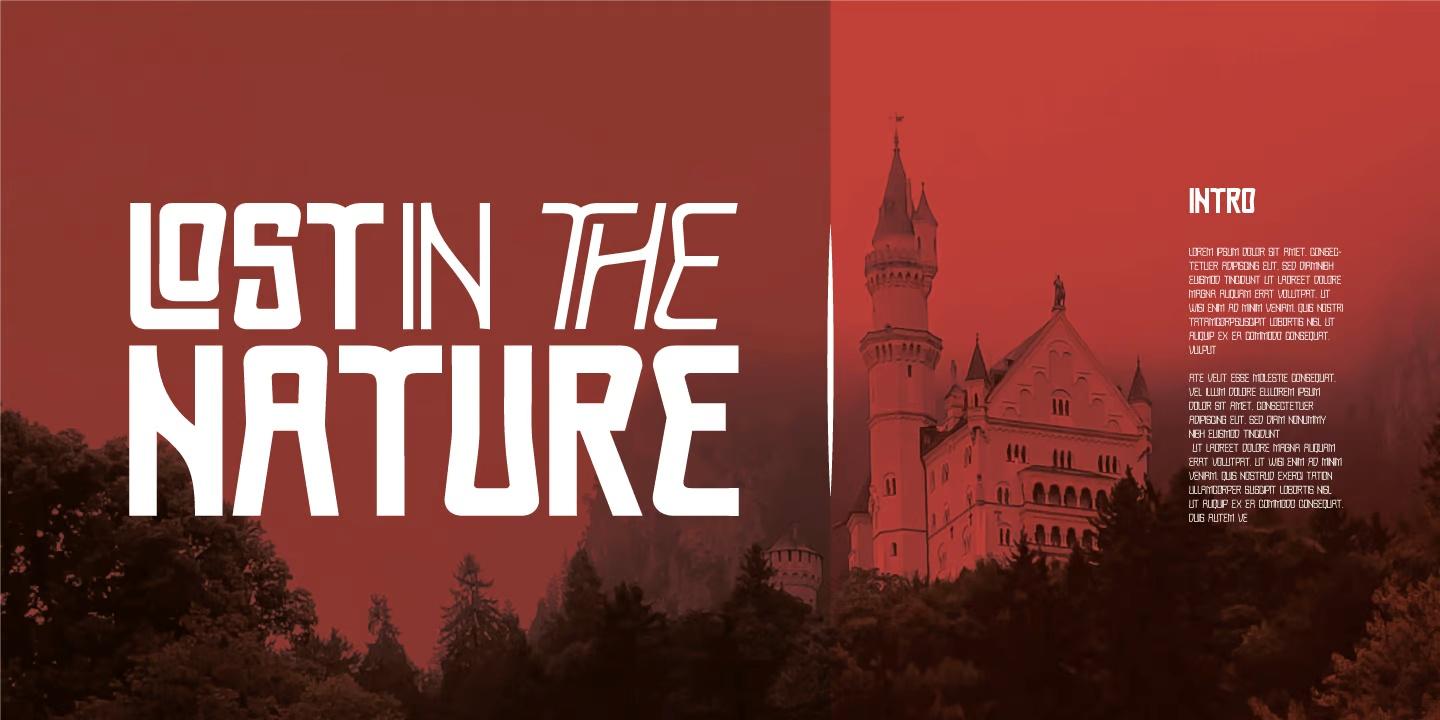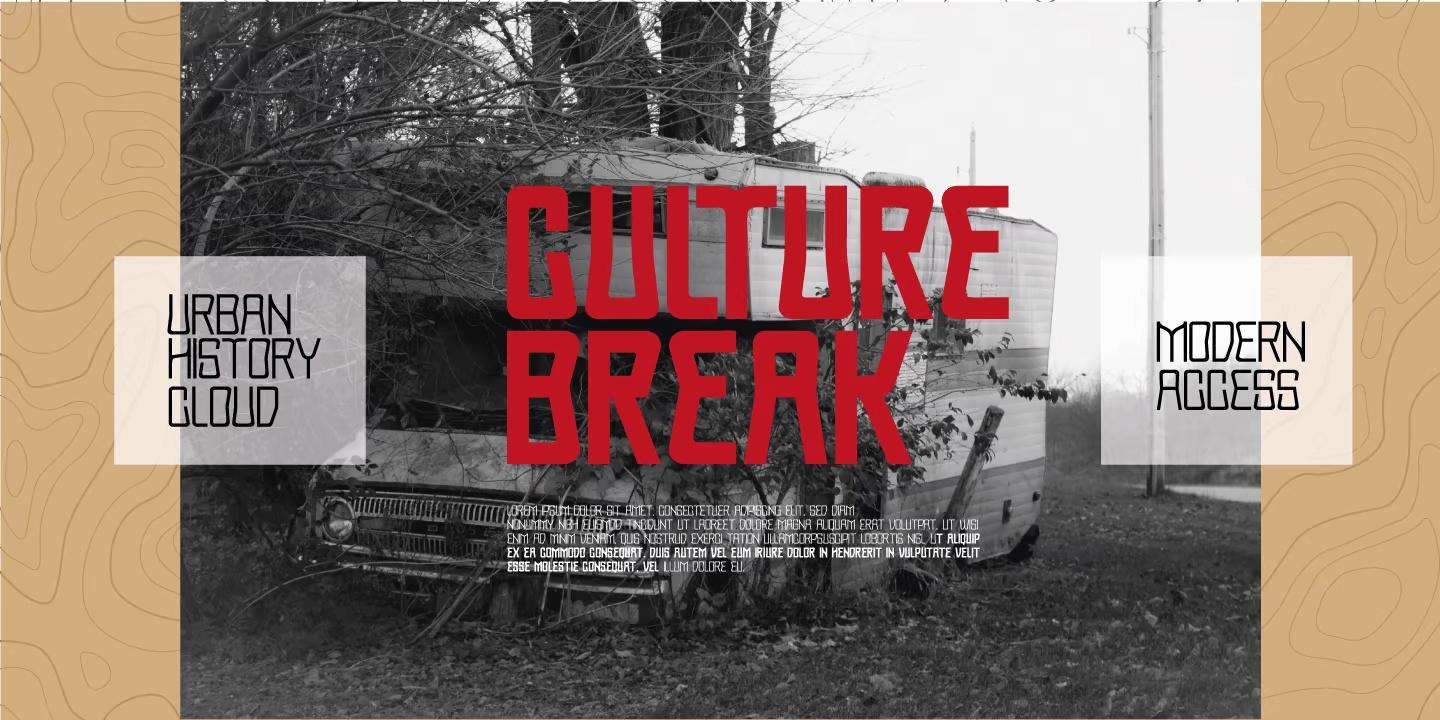
Proach Font
Description de Proach Font
Poarch est une police condensée propre et moderne, la police bien conçue comme une police sans empattement avec toutes les majuscules. Il a un angle de pointe arrondi et un style différent d’une police sans en commun. La police est parfaite pour tout projet tel qu’un en-tête de brochure/magazine, un slogan de logo, des titres de dépliants et elle peut également être une police de texte de paragraphe.